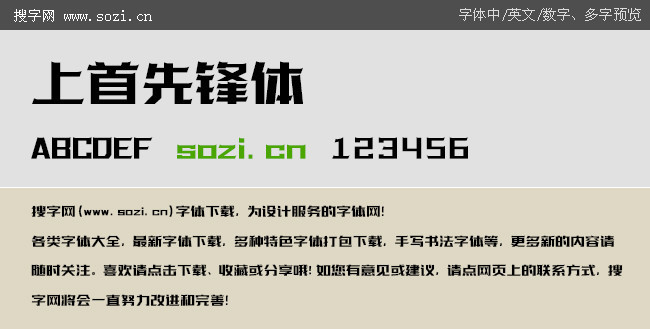
上首先鋒體
搜字網(wǎng)給大家提供一款上首先鋒體中文字體下載,上首先鋒體字體筆畫穩(wěn)重,橫豎筆粗細(xì)對比對視覺造成沖撞,整體添加特點(diǎn)橫平豎直,字體風(fēng)格穩(wěn)重大氣,部分筆畫作了細(xì)節(jié)處理。適用于搭配標(biāo)志、廣告標(biāo)語、商業(yè)廣告等廣告設(shè)計(jì)。